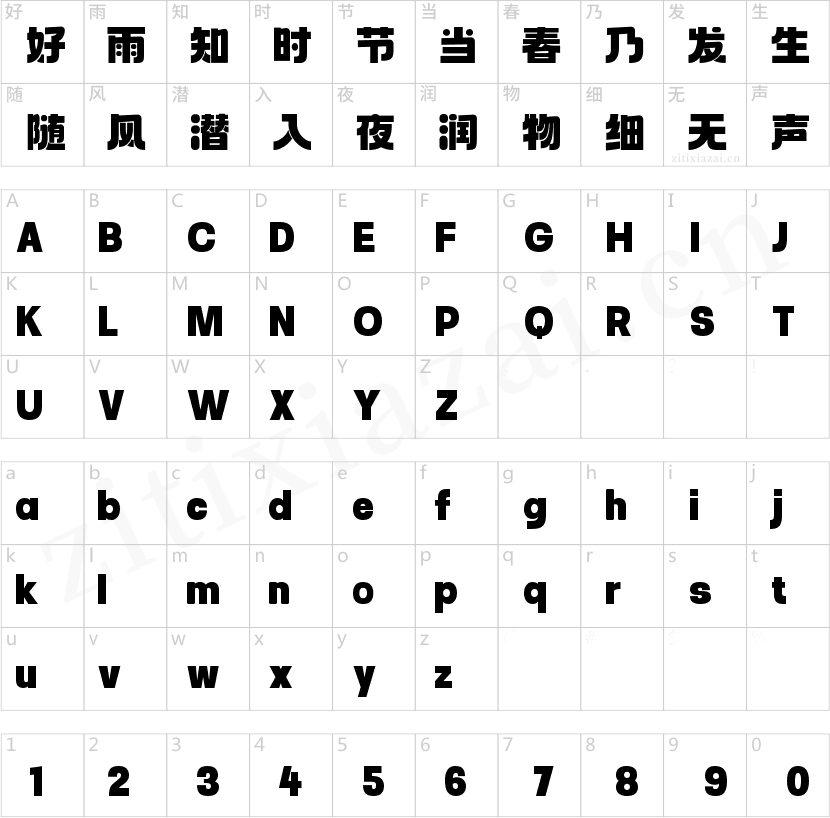
字魂鱼丸体
字魂鱼丸体,这款字体结构工整、笔画清晰,兼顾美观与易读性,适用于标题、正文、海报、包装、LOGO 等多种场景。字形优雅稳定,风格百搭耐看,适配日常排版与创意设计,让文字呈现更舒适、更具质感。字魂鱼丸体一笔一画,皆是细节,以均衡的比例、流畅的线条打造舒适视觉体验,字形端正大气,风格简约现代。无论是商业设计、品牌宣传还是日常排版,都能轻松驾驭,让文字更有格调与力量。字魂鱼丸体字体下载。